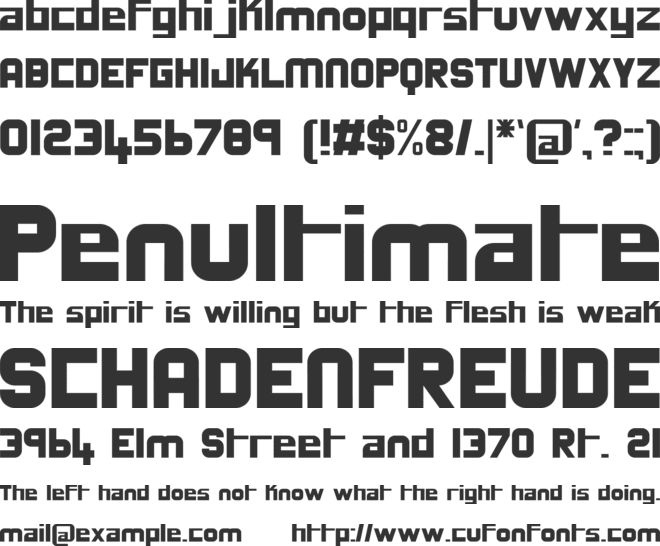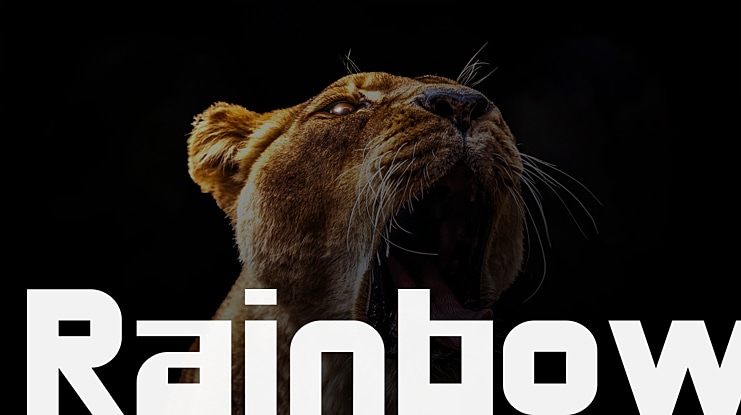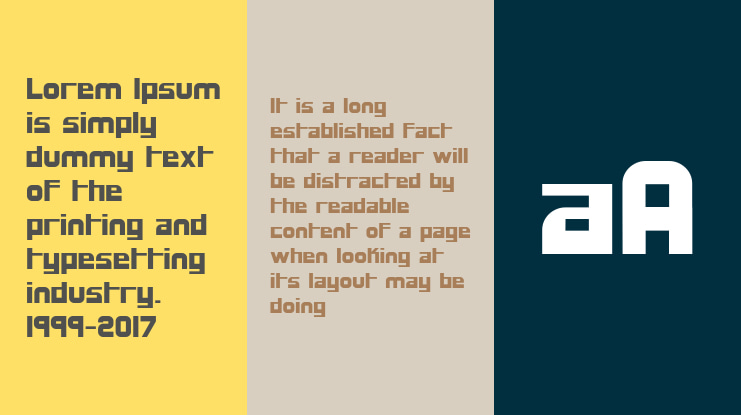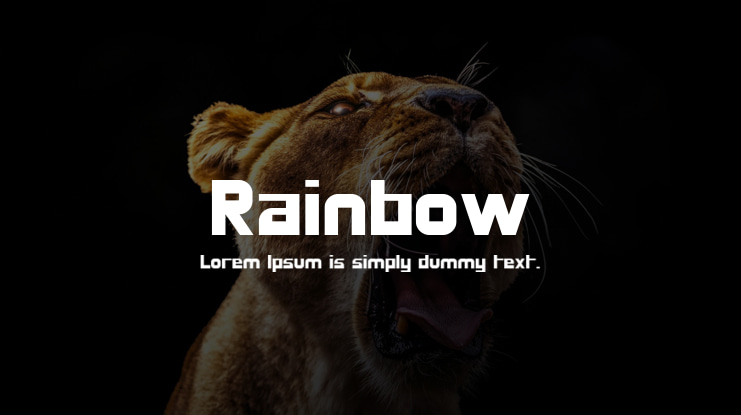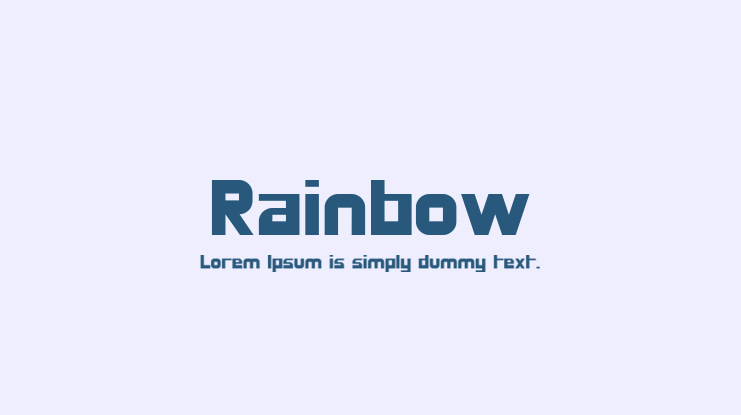
Rainbow Font
P.A.Vannucci
Mattoncini e fantasia, per un font imperdibile che unisce l’ornamento geometrico con il giardino della fantasia nella tipografia moderna. Un font True Type che non deve mancare nella vostra collezione di font indispensabili.